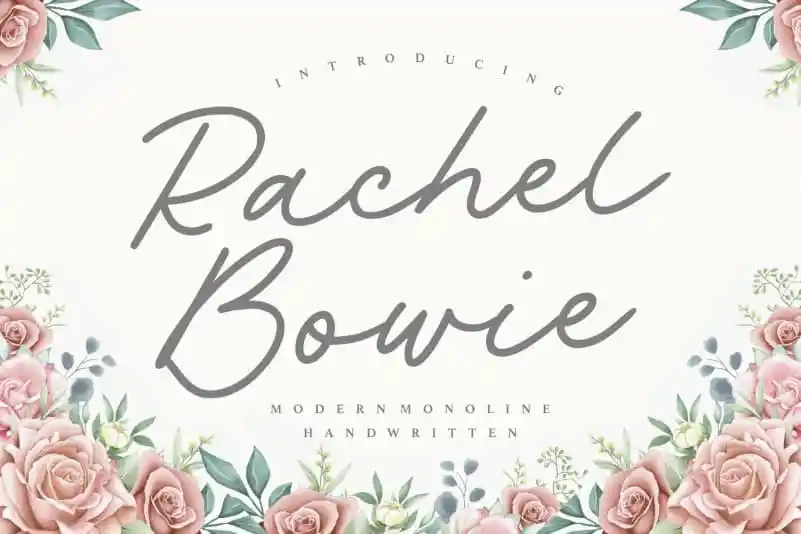
Rachel Bowie Monoline Handwritten Font – Download Grátis
A fonte Rachel Bowie Monoline Handwritten é perfeitamente adaptada para criar uma experiência visual agradável e envolvente em qualquer aplicação visual. Suas linhas fluídas e elegantes, criadas com um toque de escrita livre e natural, permitem um ar pessoal que pode ser usado de várias maneiras — desde embalagens de produto até projetos de marca, revistas, redes sociais, casamentos ou qualquer outra aplicação onde você deseja expressar uma mensagem acima de fundo. Com seu estilo único e despojado, a Rachel Bowie Monoline Handwritten é perfeita para aquelas pessoas que buscam um toque autêntico em suas criações visuais. Ideal tanto para designers como para aqueles que simplesmente apreciam um design cuidadosamente pensado, essa fonte oferece uma maneira de expressar seu próprio estilo e personalidade no meio dos designs digitais.